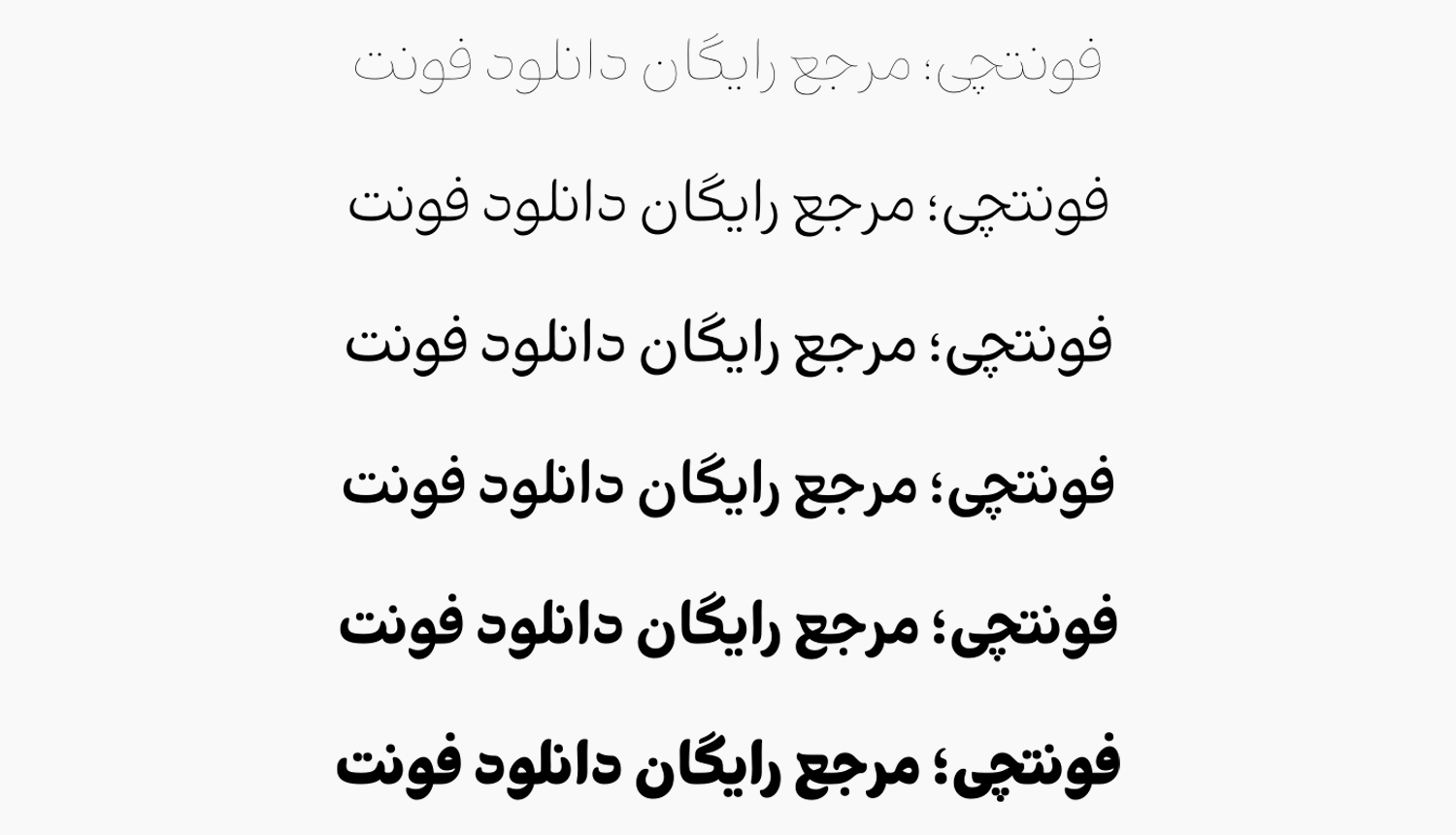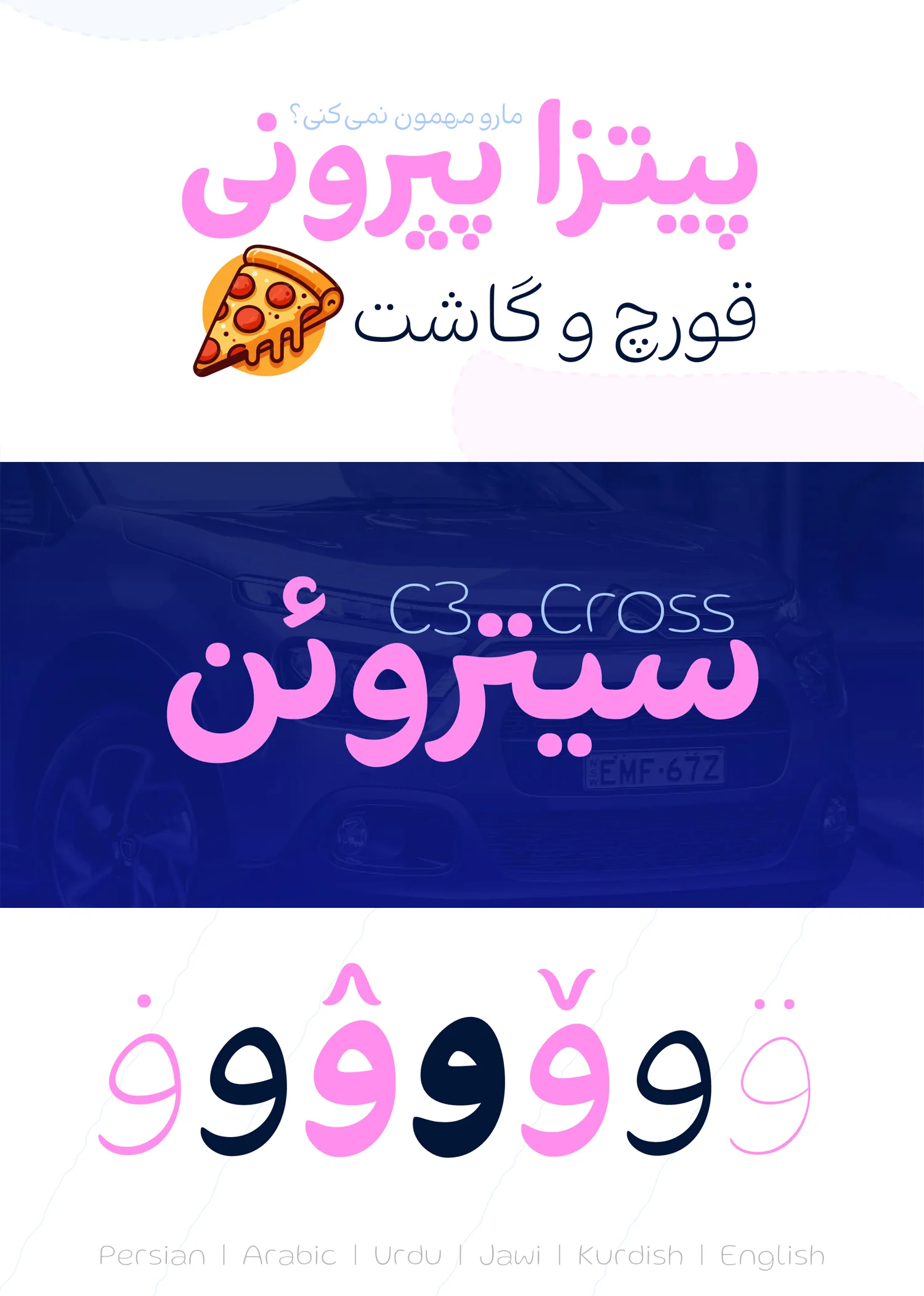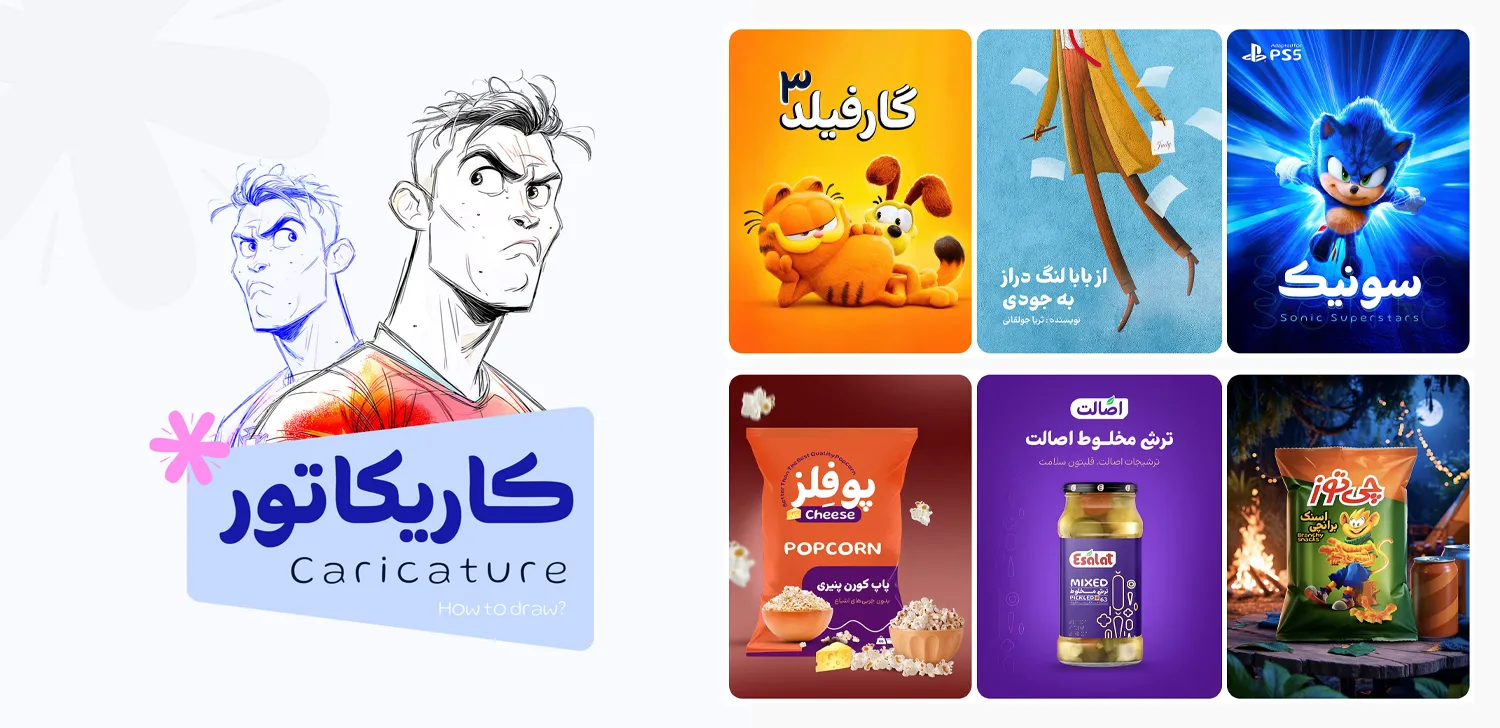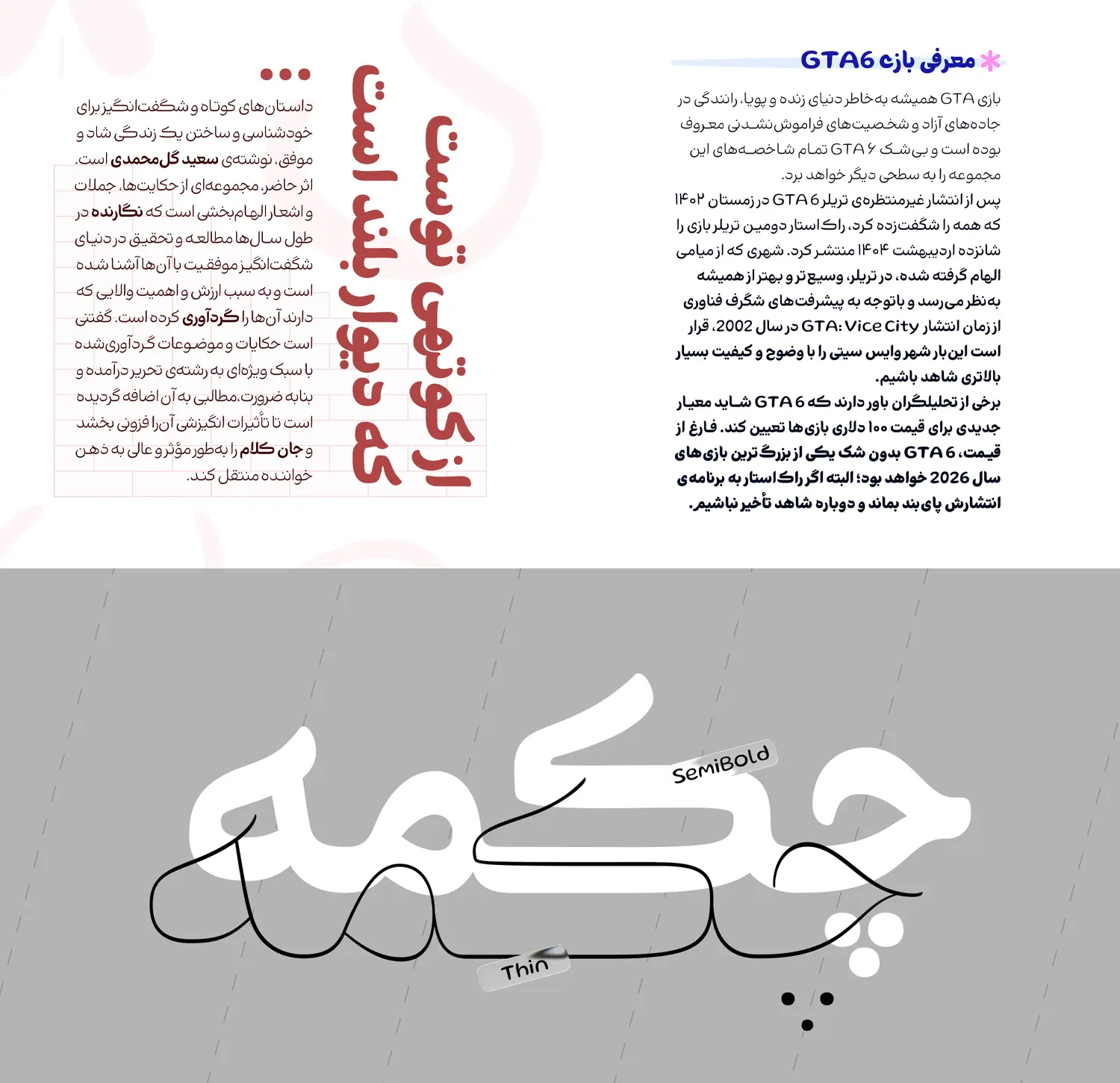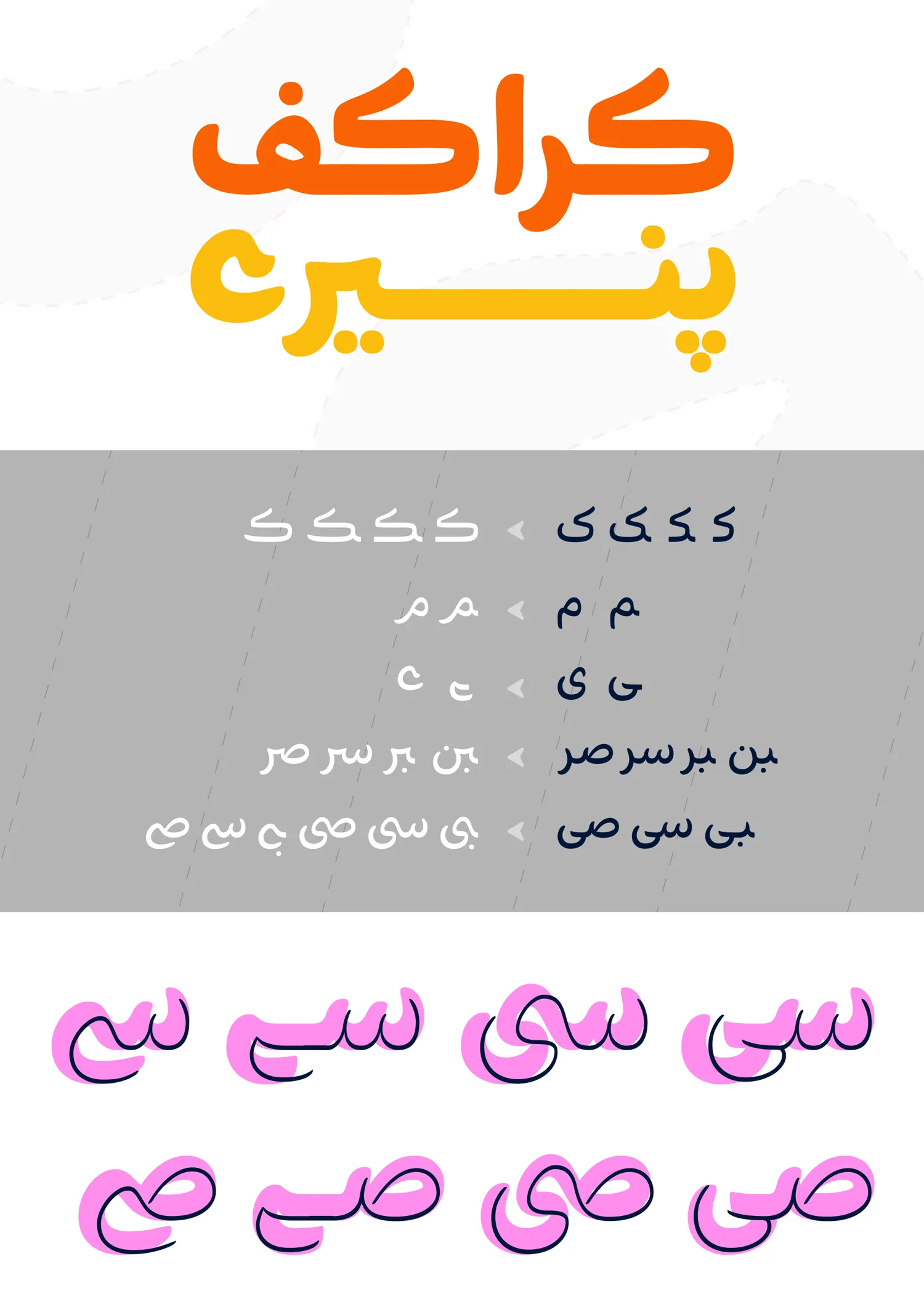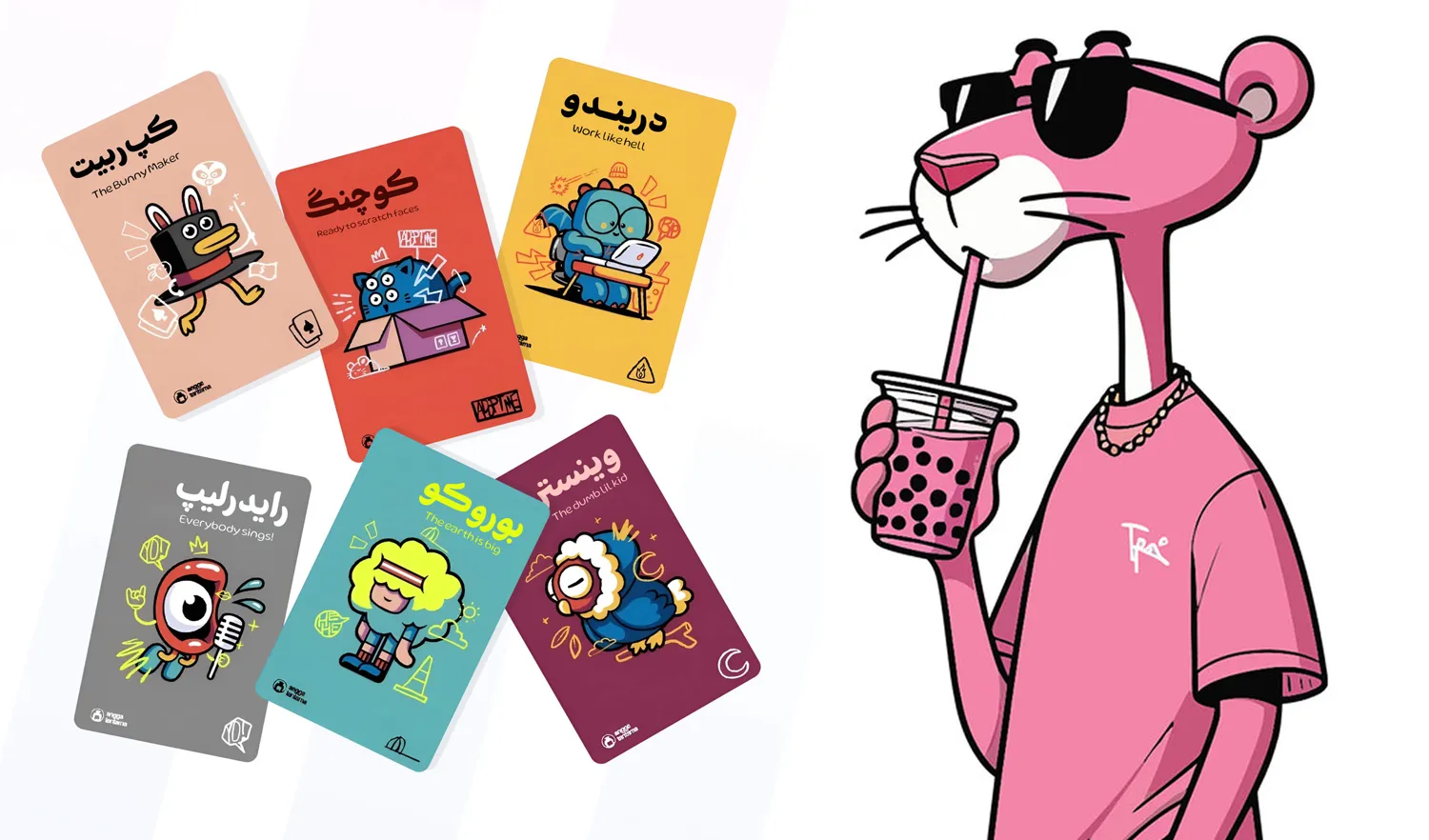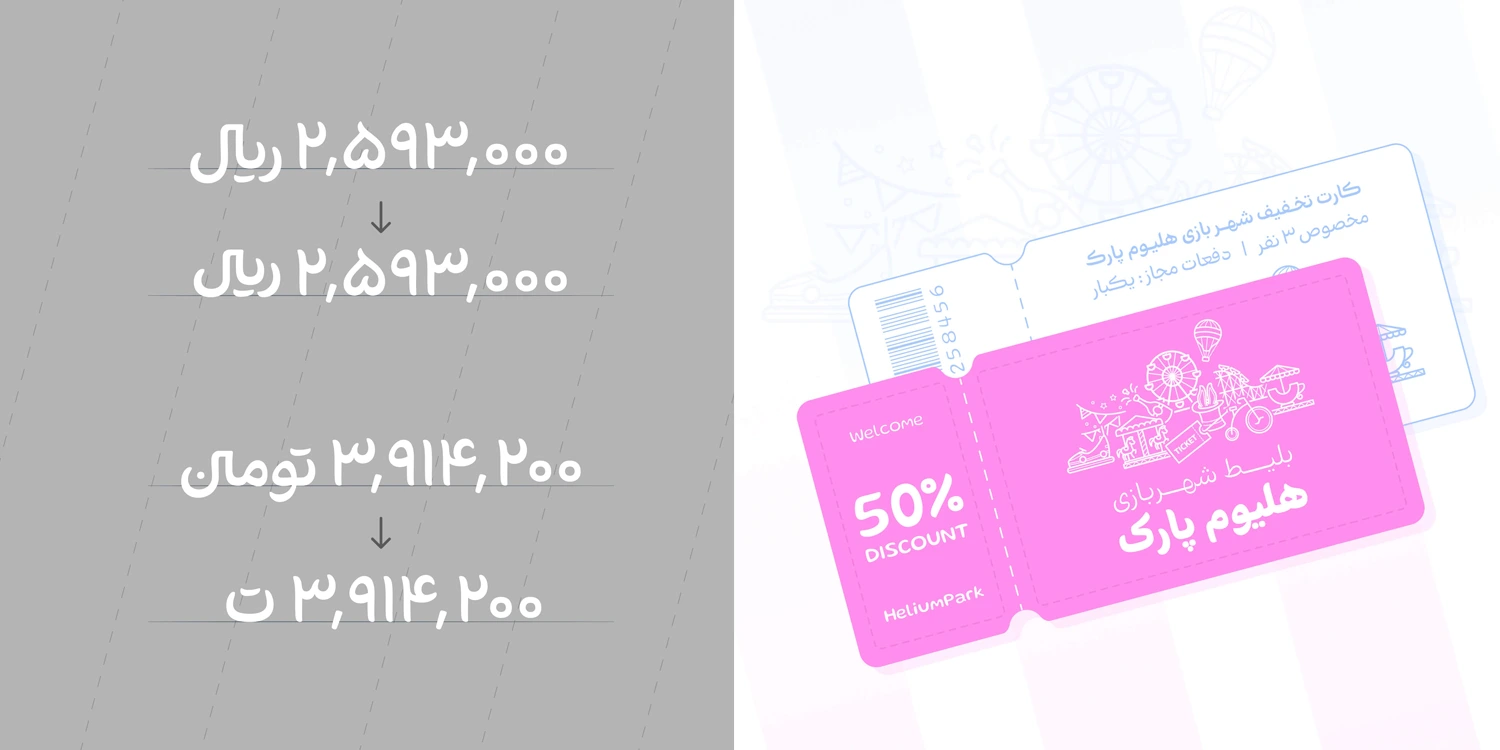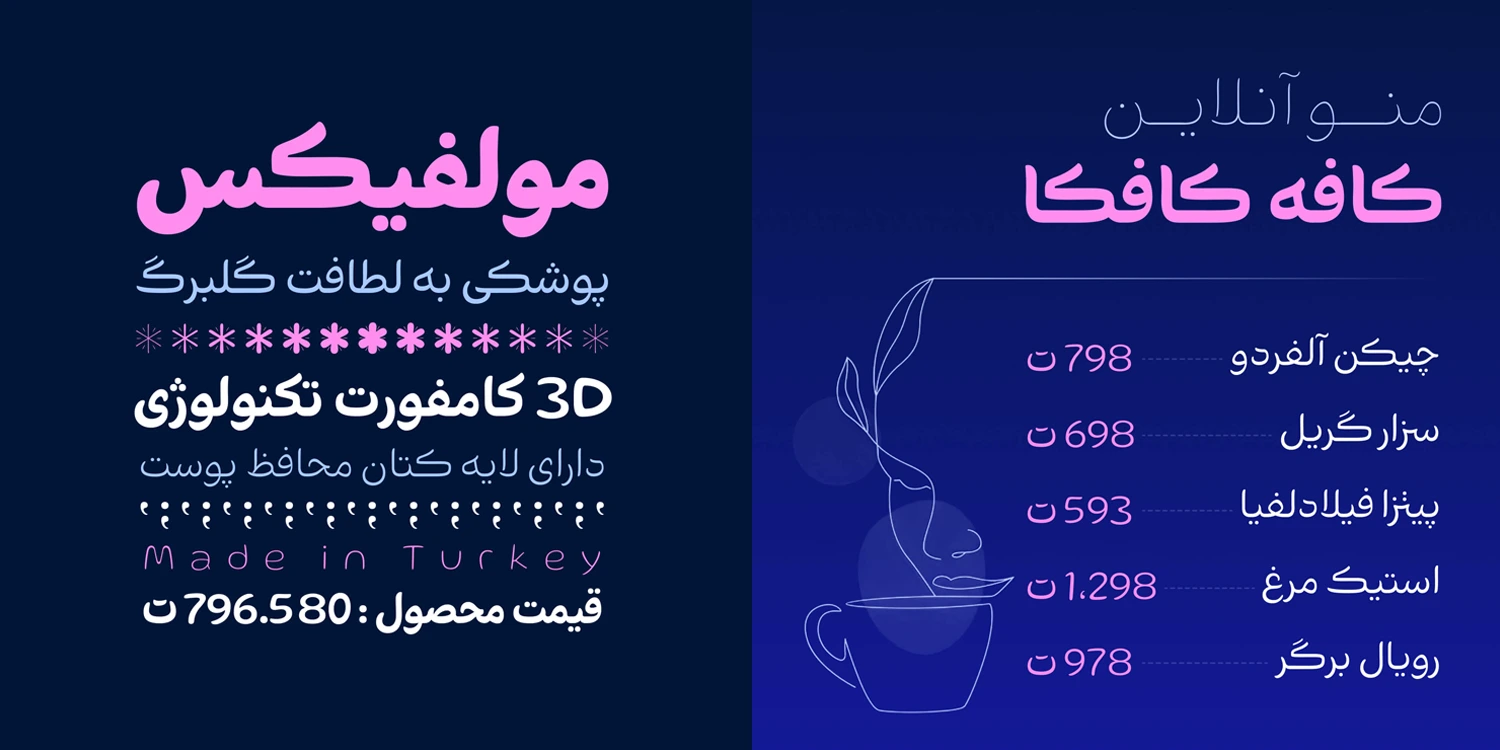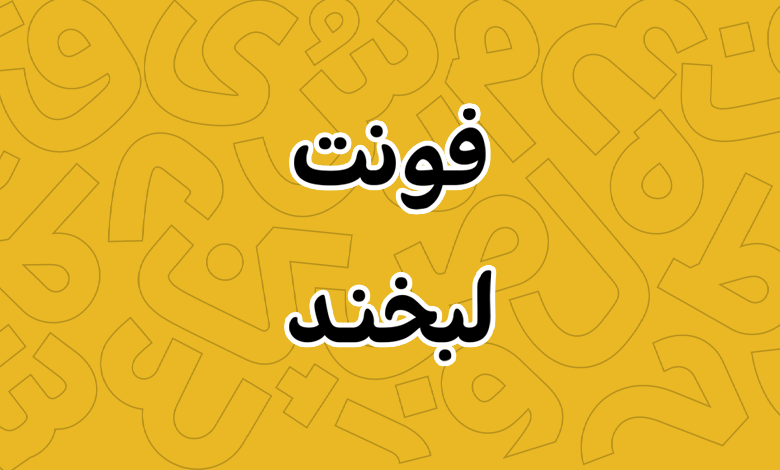
فونت لبخند (Labkhand)
فونت لبخند (به انگلیسی: Labkhand) از سری فونتهای دستنویس جدید فارسی است که با پشتیبانی از ۶ وزن متنوع و دارای متغیر وزنی در نسخه وریبل، میتواند انتخاب مناسبی برای متون و تبلیغات باشد. این فونت با الهام از سادگی و صمیمیتی که در دستخطهای شخصی وجود دارد الهام گرفته شده است.
در طرای حروف این فونت لطافت و نرمی ارجحیت فراوان داشته است؛ بهطوری که گوشههای سرتاسری نرم، چشمیهایی با ترکیب از دایره و مثلث و تغییراتی جزئی در انتهای کشیدگی و زوایای حروف پیاده سازی شده تا روی این مسئله تاکید کند.
از اینرو با فونتی مواجه هستیم که برای استفاده در فضاهایی که نیاز به صمیمیت و شخصیت دارند عملکردی الی دارد. حال این محیط میتواند متون بلند و کوتاه یک کتاب یا مجله داستانی سرگرم کننده برای کودک و نوجوان باشد یا اینکه بر روی بستهبندی محصولات، تصویر تامنیل شبکههای اجتمای یا طراحی پوسترها در تبلیغات محیطی مورد استفاده قرار گیرد.
فونت فارسی لبخند محدود به این زبان نیست و از همین ساختار نرم و دستنویس خود در سایر زبانهای انگلیسی، کوردی، اردو، عربی و جاوی پشتیبانی کاملی دارد. علاوه بر وزنهای ۶ گانه خود، نسخه مخصوص برای اعداد فارسی هک شده و نسخه مخصوص بدون حروف و اعداد انگلیسی نیز هر یک در پوشه جداگانه قرار دارند. علاوهبر این از اعداد همعرض و اعداد پایینرونده هم پشتیبانی میکند.
از دیگر خصوصیات فونت لبخند میتوان به پشتیبانی از حروف و ترکیبات جایگزین اشاره کرد که شامل مواردی مثل «کـ، ـکـ، ـک، ک، ـم، م، ـی، ی، ـبن، ـبر، ـسر، ـصر، ـبی، ـسی، ـصی» است. فونت لبخند توسط برادران حیدری طراحی شده است. در ادامه تصاویری از این فونت زیبا را مشاهده کنید.